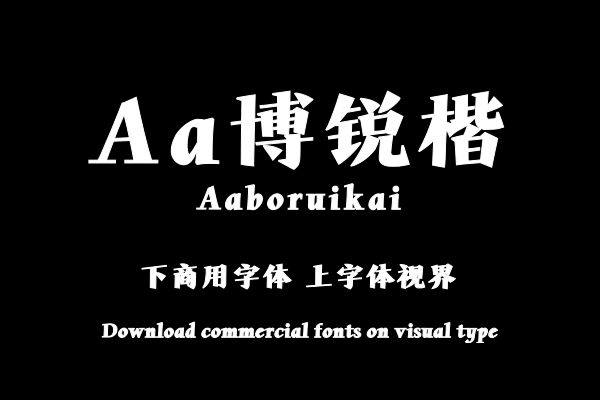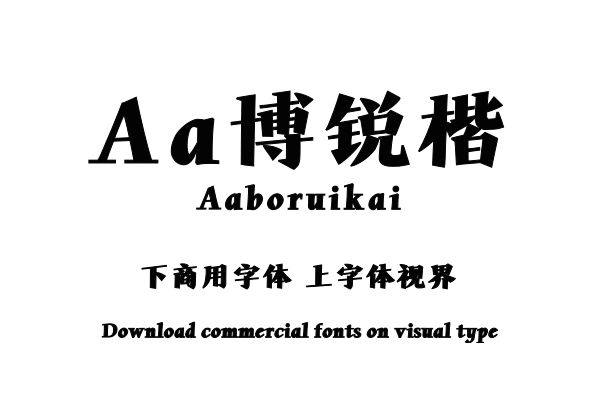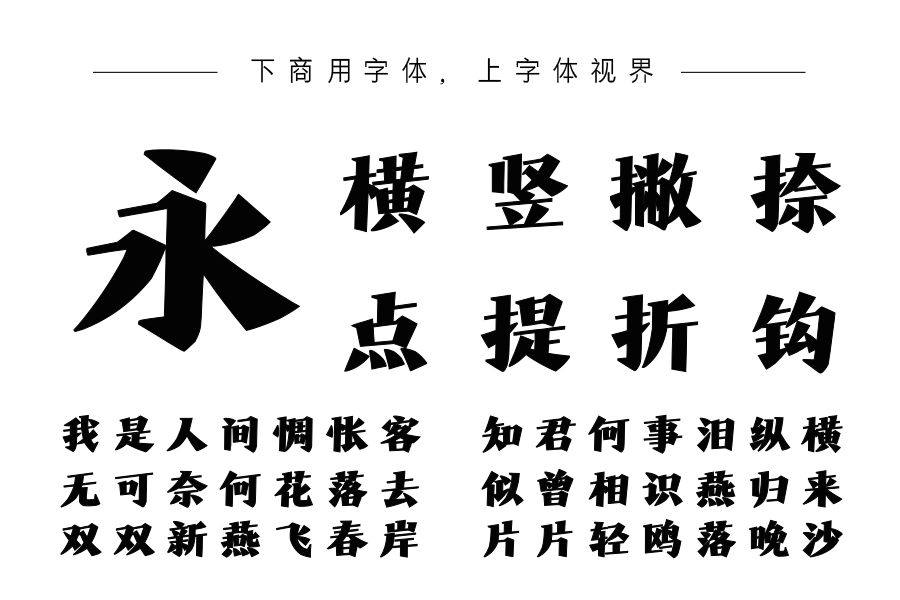
这款字体将楷书的书写风格与宋体的设计元素结合,既保留了楷书的流畅与自然,又融入了宋体的结构与美感,使这套字体在保持古典气质的同时,展现出充满人文气息与灵动的特点......购买须知:“下载服务费”与“字体VIP”所获得字体 仅用于个人非商用, 商用请联系付费授权。本字体为电脑用字,手机没有root权限不支持直接手机换字(手机如何root,请自行百度搜索教程)。购买前请先 了解清楚后再付款 ,字体为虚拟产品无法回收 一旦购买不支持退款。